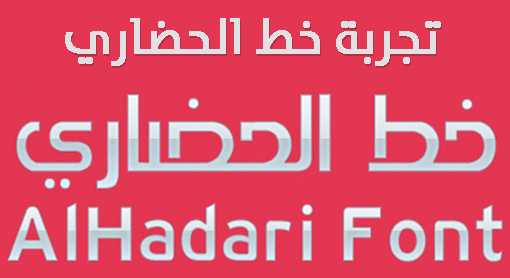
معاينة خط الحضاري
نبذه تعريفيه عن خط الحضاري
خط الحضاري هو من ضمن مكتبة الخطوط العربيه الحديثه وهو من أروع وأجمل الخطوط العربية الحديثةخط الحضاري عربي وانجليزي كلاهما أنيق وراقي ويليق بالتصاميم الفخمة الاحترافية
تم تصميم خط الحضاري بهدف كتابة العناوين في الصحف والمجلات والكتب والقنوات الفضائيه.
وهو من تصميم المصمم القدير والمبدع الأخ الفاضل : البهلول محمد أبو حميدة
وهو مصمم بشركة الحضارة للخدمات الإعلانية / طرابلس ، ليبيا .
ويتميز الخط بالجمال والأناقه
ويجمع في جماله ما بين جمال الخطوط العربيه القديمه وجمال الخطوط العربيه الحديثه